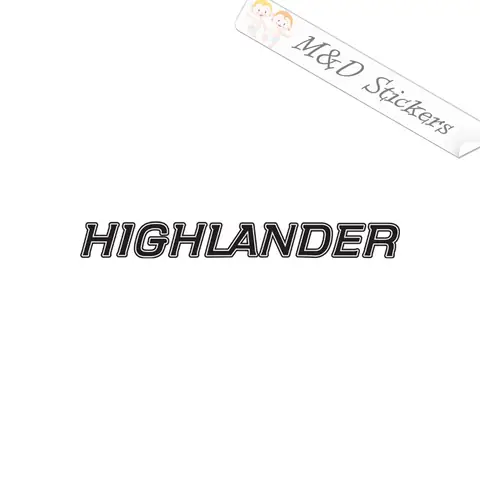
Font Toyota Highlander: Khám Phá Kiểu Chữ, Thiết Kế Và Ứng Dụng Trong Thế Giới Đồ Họa
Giới thiệu chung về font Toyota Highlander
Trong thời đại mà thương hiệu không chỉ thể hiện qua logo, màu sắc mà còn qua từng chi tiết nhỏ như kiểu chữ (font), việc nghiên cứu và hiểu rõ font Toyota Highlander trở thành một nhu cầu thiết yếu đối với các nhà thiết kế, marketer và những người yêu thích xe hơi. Khi nhắc đến Toyota Highlander – một trong những mẫu SUV hạng trung‑cao của Toyota – hầu hết người tiêu dùng sẽ nghĩ ngay đến sự sang trọng, tiện nghi và công nghệ tiên tiến. Tuy nhiên, ít người để ý rằng cách Toyota lựa chọn kiểu chữ cho mẫu xe này cũng góp phần không nhỏ vào việc xây dựng hình ảnh thương hiệu mạnh mẽ, đồng thời tạo nên sự nhất quán trong mọi tài liệu quảng cáo, brochure, website và các tài sản truyền thông khác.
1. Lịch sử và nguồn gốc của font Toyota Highlander
1.1. Toyota và tầm quan trọng của typographic identity
Toyota, một trong những tập đoàn ô tô lớn nhất thế giới, luôn chú trọng tới việc xây dựng hệ thống nhận diện thương hiệu (brand identity) chặt chẽ và nhất quán. Một phần quan trọng của hệ thống này là typography – cách sử dụng chữ để truyền tải thông điệp, tạo cảm xúc và định vị thương hiệu trên thị trường. Từ những năm 1990, Toyota đã bắt đầu hợp tác với các công ty thiết kế danh tiếng để tạo ra những font riêng biệt, phù hợp với từng dòng sản phẩm.
1.2. Sự ra đời của font Toyota Highlander
Khi Toyota quyết định ra mắt mẫu SUV Highlander (còn được biết đến với tên gọi “Toyota Kluger” ở một số thị trường), đội ngũ marketing và design đã muốn một kiểu chữ phản ánh độ mạnh mẽ, hiện đại và sang trọng – những giá trị cốt lõi của mẫu xe. Để đạt được điều này, họ đã lựa chọn một font sans‑serif tùy biến, dựa trên nền tảng của font Toyota Type, một bộ font nội bộ được Toyota phát triển từ năm 2008.
Font Toyota Highlander được hoàn thiện vào năm 2013, đồng thời được áp dụng trong các tài liệu quảng cáo, catalogue, website chính thức và các biển hiệu showroom. Đặc điểm nổi bật của nó là độ cân bằng giữa tính năng động và tính thanh lịch, giúp tạo cảm giác “điểm nhấn” nhưng không gây rối mắt.
1.3. Quá trình tinh chỉnh và phiên bản cập nhật
Từ khi ra mắt, font đã trải qua ba lần cập nhật chính:
• 2013 – Phiên bản gốc: Được thiết kế để phù hợp với các tài liệu in ấn và website desktop.
• 2016 – Phiên bản “Highlander 2.0”: Thêm vào các ký tự mở rộng (Latin extended, Cyrillic) để đáp ứng nhu cầu thị trường châu Á‑Âu.
• 2020 – Phiên bản “Highlander UI”: Tối ưu hoá cho giao diện người dùng (UI) trên các thiết bị di động, giảm độ dày nét chữ để cải thiện độ đọc trên màn hình nhỏ.
Mỗi lần cập nhật đều được thực hiện dựa trên phản hồi của người dùng, nhà thiết kế và các chuyên gia typographic, nhằm đảm bảo rằng font luôn đáp ứng được tiêu chuẩn độ rõ nét, tính nhất quán và khả năng tương thích đa nền tảng.
2. Đặc điểm thiết kế và cấu trúc của font Toyota Highlander
2.1. Kiểu chữ (typeface) – Sans‑Serif
Toyota Highlander sử dụng một sans‑serif – không có các “gót” (serif) ở đầu và cuối các nét chữ. Điều này mang lại cảm giác hiện đại, sạch sẽ và dễ đọc. Các nét chữ được thiết kế thẳng và cân đối, giảm thiểu sự phức tạp, phù hợp với phong cách thiết kế “minimalist” đang thịnh hành trong ngành ô tô.
2.2. Trọng lượng (weight) và độ dày (stroke)
Font bao gồm bốn trọng lượng chính:
Trọng lượngMô tảỨng dụng thường
Light (300)Mỏng, nhẹ, phù hợp cho body textBrochure, mô tả kỹ thuật
Regular (400)Trọng lượng trung bìnhTiêu đề phụ, nội dung website
Bold (700)Đậm, nổi bậtTiêu đề chính, CTA (Call‑to‑Action)
Black (900)Rất đậm, mạnh mẽBiển quảng cáo, banner lớn
Sự đa dạng về trọng lượng cho phép designer linh hoạt trong việc tạo ra hierarchy (cấp bậc) nội dung, đồng thời duy trì tính thống nhất trong toàn bộ hệ thống nhận diện.
2.3. Tỷ lệ và khoảng cách (proportion & kerning)
• X‑height (độ cao của các chữ thường như “x”) chiếm khoảng 55% của chiều cao tổng thể, giúp tăng độ đọc trên các màn hình.
• Cap height (độ cao của các chữ in hoa) được cân bằng với baseline để tạo cảm giác vững chắc.
• Kerning (khoảng cách giữa các ký tự) được tối ưu hoá cho các cặp ký tự thường xuất hiện trong tên “Toyota Highlander” như “T‑o”, “y‑o”, “H‑i”. Điều này giúp logo và tiêu đề trông liền mạch, không có khoảng trống bất thường.